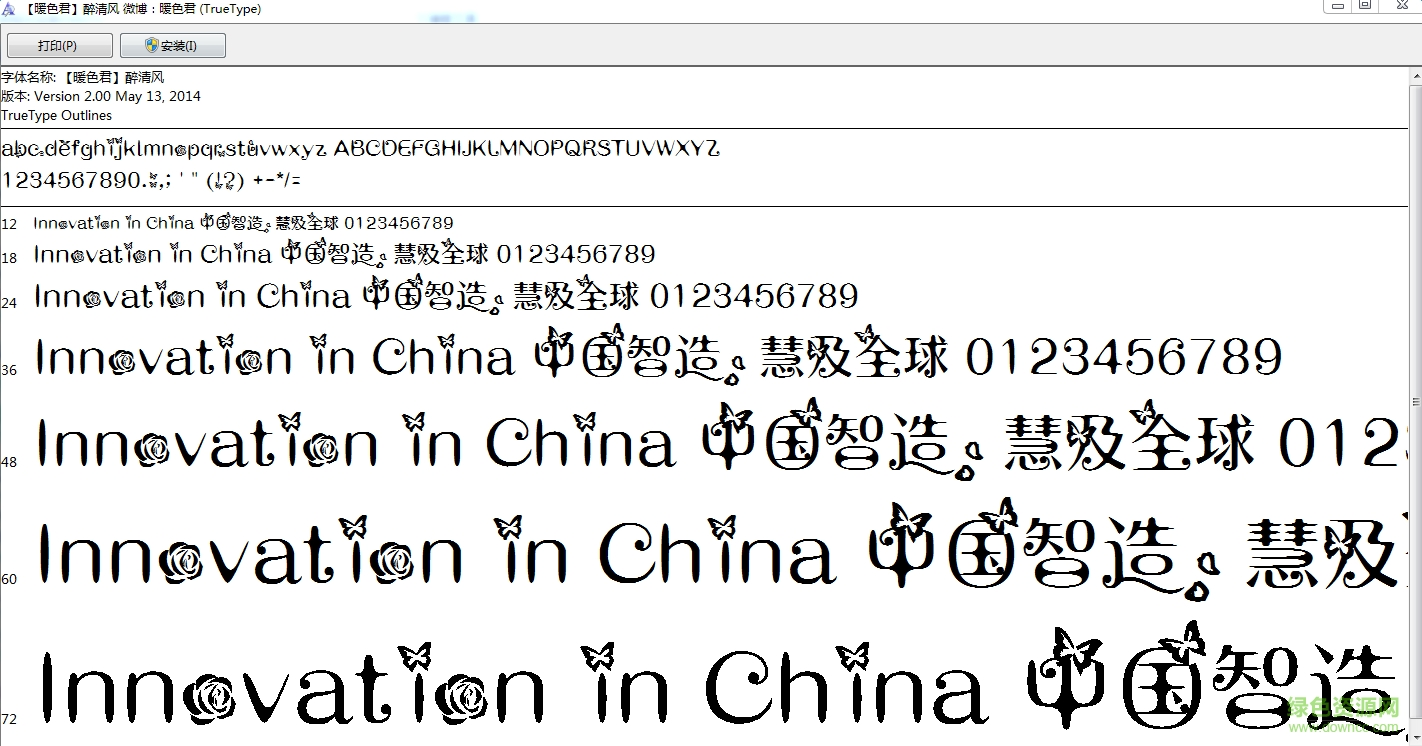
蝶醉清風(fēng)字體是一款非常花俏的藝術(shù)字體,字體圓潤(rùn),筆畫(huà)帶勾,字形中融入了特別的蝴蝶和玫瑰花元素,文案更加生動(dòng)有趣,喜歡的小伙趕緊來(lái)綠色資源網(wǎng)下載收藏吧!
蝶醉清風(fēng)字體是一款用于花紋設(shè)計(jì)方面的字體,字形唯美哥特,喜歡的朋友就下載看看吧,相信你會(huì)喜歡上這款非主流個(gè)性字體的。